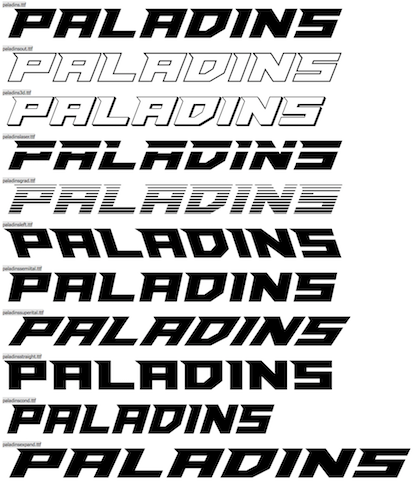
Wie heisst der Schriftzug (Grenzgaenger)
Weiss jemand wie der Schriftzug heisst also die Schrift Art (Arial und Co.)
Es ist der neue der Grenzgaenger, im Shop gibt es einige Produkte mit der Schriftzugart, ich mag die Art sehr und würde gerne was damit gravieren lassen allerdings mit andern Buchstaben und dafür brauche ich den Namen der Schriftzugart.
Gut möglich, dass jemand diese gerade einmal 6 Buchstaben ohne Vorlage gezeichnet hat.
Solche Schriften, die für ein Logo mit nur wenigen Buchstaben gezeichnet wurden, durchaus auch von bekannten, ja selbst berühmten Schriftgestalter speziell für ein Markenlogo erstellt, kranken oft daran, das man nicht für alle Buchstaben des Alfabetes eine schlüssige Form zum Stil der Schrift findet.
Auch bei dieser Schriftart denke ich, das ích da bei einigen Buchstaben Probleme hätte, die richtige Form zu finden.
Die 6 Buchstaben A E G N R und Z dürften jedoch auf einem vektorgrafik-Programm in weniger als einer halben Stunde gezeichnet sein, aber schon beim B hätte ich Probleme